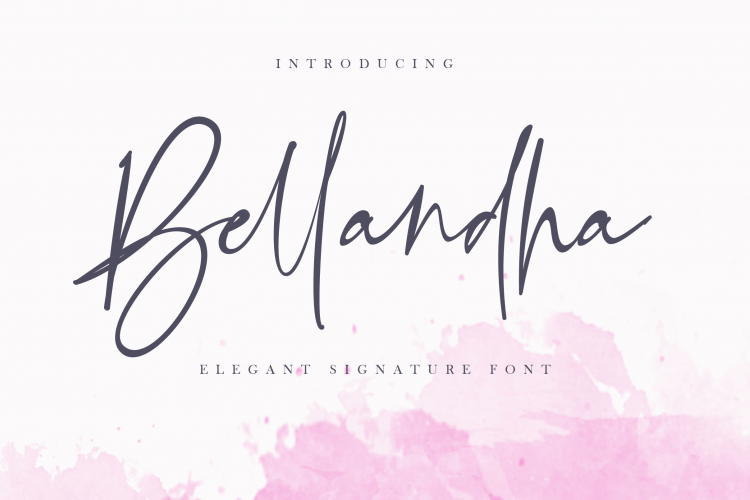
Bellandha Signature Script Font – Download Grátis
A Bellandha Signature Script Font é uma elegante e sofisticada opção para quem busca uma fonte de escrita autêntica que transmite seriedade e criatividade ao mesmo tempo. Criada pelo designer Silverdav, essa fonte foi totalmente desenhada a mão com foco em reproduzir o realismo da escrita humana. Um dos seus elementos principais é a adição de ligaturas personalizadas, que permitem uma pontualização única e autêntica que fazem a diferença no resultado final. Com sua elegância contagiante e graça natural, a Bellandha é perfeita para projetos de marca e logotipos, embalagens de produtos e frases escritas à mão. Além disso, ela se destaca como uma escolha ótima para qualquer projeto que necessite de um touch autêntico e criativo do seu próprio estilo.